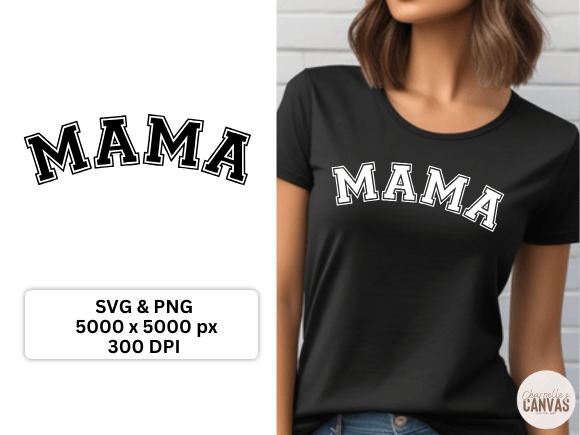
Mama Typography College Font Design
การค้นหาองค์ประกอบการออกแบบที่เหมาะสมอาจเป็นเรื่องท้าทาย แต่ Mama Typography College Font Design นำเสนอคอลเลกชันที่โดดเด่นซึ่งช่วยยกระดับงานของคุณได้ทันที
สร้างขึ้นอย่างแม่นยำ Mama Typography College Font Design ให้เวกเตอร์ที่สะอาด พิมพ์ตัวอักษรที่ราบรื่น และใบอนุญาตเชิงพาณิชย์เพื่อความสบายใจ
ไม่ว่าคุณจะสร้างผลิตภัณฑ์ POD (Print on Demand) คำเชิญงานแต่งงาน หรือกราฟิกโซเชียลมีเดีย Mama Typography College Font Design ก็เหมาะสมอย่างยิ่ง